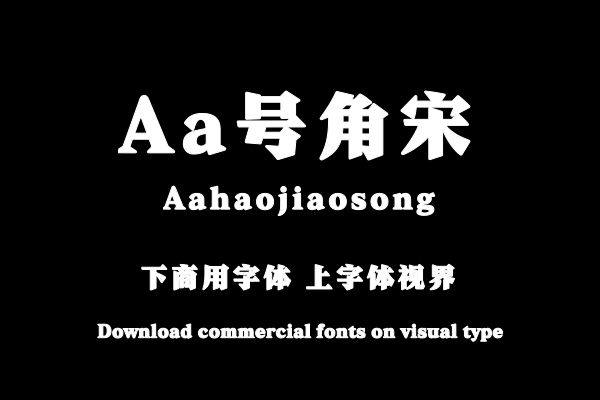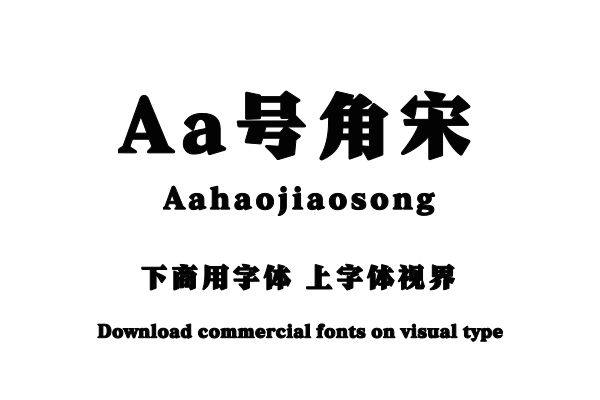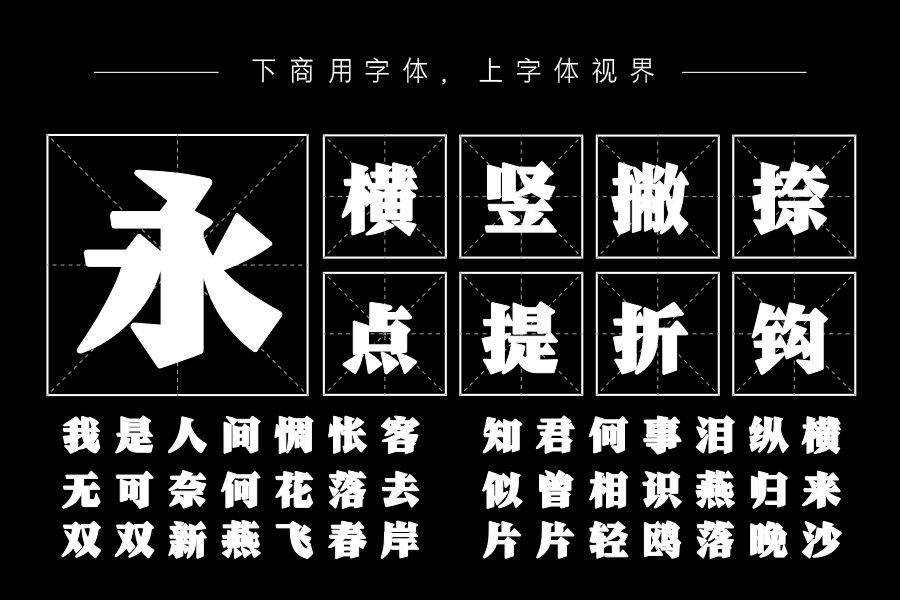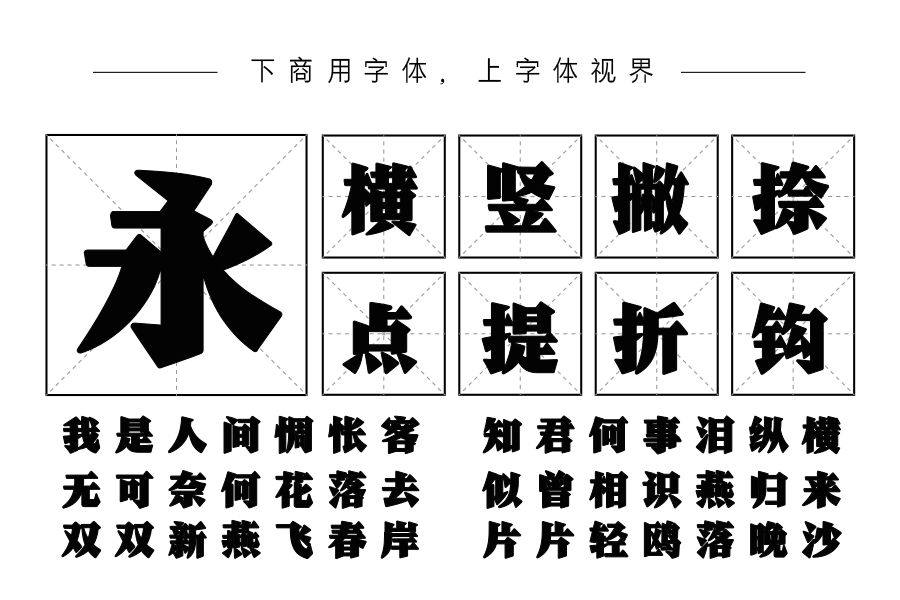
用三角元素强化衬角点划,形成一款醒目有力的宋体。购买须知:“下载服务费”与“字体VIP”所获得字体 仅用于个人非商用, 商用请联系付费授权。本字体为电脑用字,手机没有root权限不支持直接手机换字(手机如何root,请自行百度搜索教程)。购买前请先 了解清楚后再付款 ,字体为虚拟产品无法回收 一旦购买不支持退款。